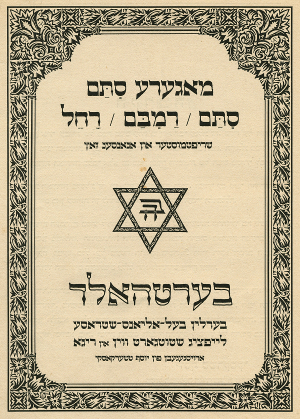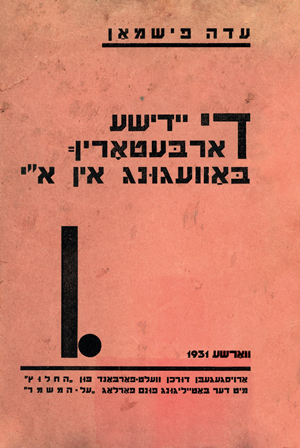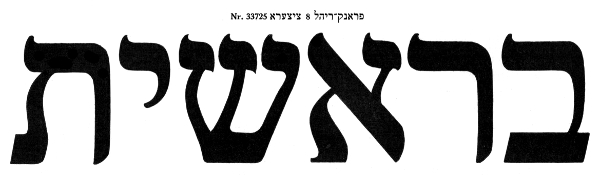
Hebräische Schriftgestaltung im Kontext von Buchkunstbewegung und ‹Neuer Typographie›
Unter dem Schlagwort der ‹Neuen Buchkunst› formierten sich in Deutschland um 1900 Bestrebungen zu einer Erneuerung der Buch- und Schriftgestaltung nach dem Vorbild der englischen Arts-and-Crafts-Bewegung. Diese Erneuerungsbewegung verstand sich als Reaktion auf die in Deutschland vor allem nach der Reichsgründung 1871 rasant vorangetriebene Industrialisierung. Die Ablösung der handwerklich-traditionellen durch eine zunehmend technisierte Produktion betraf neben diversen Gütern des täglichen Gebrauchs auch die Buchherstellung. Folgt man den zeitgenössischen Kommentatoren führte dies zu einem qualitativen Niedergang der neben dem Material auch die Ästhetik betraf. Neben den verschiedenen industriell hergestellten Gütern wurde um die Jahrhundertwende auch beim Buch die Forderung nach einer zeitgemäßen, material- und zweckgebundenen Form laut. Diese Forderung betraf all seine Elemente und nicht zuletzt auch die Druckschriften. So wurde damit begonnen zur Schriftgestaltung Künstler herbeizuziehen. Die auf diese Weise erzielten Resultate waren in einer ersten Phase noch stark von der Formensprache des Jugendstils beeinflusst. Nach Ende des Ersten Weltkriegs setzte dann allerdings eine deutliche Hinwendung zu historischen, stärker handschriftbasierten Formen ein. Dies verdankte sich zu einem großen Teil dem Einfluss des englischen Schriftkünstlers Edward Johnston. Der an der Londoner School of Arts and Crafts lehrende Johnston und seine auf den Formen alter Handschriften fussende kalligraphische Methode war in Deutschland vor allem durch das Wirken seiner Schülerin und Übersetzerin Anna Simons bekannt geworden. In der Folge wurden Fragen der Schriftgestaltung dezidiert traditionsgebunden behandelt und vor allem durch die intensive Beschäftigung mit historischen Formen bestimmt. Mit dieser Tendenz, welche das gestalterische Selbstverständnis sowohl von Franzisca Baruch als auch von Henri Friedlaender nachhaltig prägte, brach um 1925 schliesslich die ‹Neue Typographie›, die eine neue, wahrhaft industrielle Ästhetik propagierte.
Schriftgestaltung und kunstgewerbliche Ausbildung in Deutschland
Ein wichtiger Träger dieser ästhetischen Tendenz waren Kleinpressen nach dem Modell der in den 1890er Jahren von William Morris in Hammersmith bei London betriebenen Kelmscott Press. Hierbei handelte es sich um Betriebe, bei denen die Arbeitsteilung zwischen Verlag, Gestaltung und Herstellung zugunsten einer ganzheitlichen Praxis weitgehend aufgehoben war. Auf diese Weise wollte man einem möglichst idealen Einklang von Buchinhalt und Buchgestalt erreichen. Die Pressedrucke sollten als Vorbilder wirken und so dazu beitragen, die formale, handwerkliche und künstlerische Qualität von Büchern, Zeitschriften und nicht zuletzt von Druckschriften nachhaltig zu verbessern. Tatsächlich gelang es in Deutschland den Pressen sich in diesem Sinn als ‹Versuchsanstalten› zu positionieren und es sind in der Folge eine Reihe größere Unternehmen die zu Trägern der buchkünstlerischen Erneuerung werden.[1] Als beispielhaft für das erfolgreiche Zusammenspiel von bibliophiler Reformbewegung und Massenproduktion kann neben dem Insel Verlag mit seiner ‹Bücherei› auch die Schriftgießerei Gebr. Klingspor in Offenbach gelten. Das weltweit tätige Unternehmen, das 1907 auch zu den Gründern des Deutschen Werkbunds gehörte, war bekannt dafür, ausgesprochen hohen Wert auf die ästhetische Qualität seiner Schriften zu legen. In den 1920er Jahren beschäftigte das Unternehmen mit Rudolf Koch einen der herausragenden Schriftkünstler Deutschlands, der mit seiner im Rahmen dieser Zusammenarbeit entfalteten gleichsam expressiven wie im Handwerk verwurzelten Schriftgestaltung nicht nur für Henri Friedlaender ein wichtiges Vorbild war.
Anzeige für die Schriftgießerei Gebr. Klingspor unter Verwendung der Schriften ‹Neuland› und ‹Koch-Antiqua› von Rudolf Koch, 1926.
Das Vorhandensein einer graphischen Industrie mit ausgesprochenem Qualitätsbewusstsein verband sich in Deutschland zu dieser Zeit mit der Grundlagenbildung in Schriftkursen an einer Reihe von Kunstgewerbeschulen, welche die vom Werkbund ausgehenden Impulse bald aufgenommen und in die Ausbildung integriert hatten. So bestand beispielsweise in Leipzig, dem Zentrum der deutschen Buchproduktion, die Akademie für graphische Künste und Buchgewerbe.[2] Hier bewarb sich 1925 der 21-jährige Henri Friedlaender. Friedlaender hatte zu diesem Zeitpunkt bereits seit drei Jahren in einer Berliner Druckerei gearbeitet. Seinem Bewerbungsschreiben zufolge, war für ihn dabei vor allem, der Drang bestimmend, «mich in künstlerisch-handwerklicher Hinsicht so auszubilden, daß ich mit Erfolg in einer ‹Presse› oder an ähnlicher Stelle mitarbeiten kann.»[3] Für Friedlaender, der die Leipziger Akademie mit bestandener Meisterprüfung als Schriftsetzer im Juli 1926 nach weniger als einem Jahr bereits wieder verliess, war es der Unterricht in Entwerfen und Schriftkunst bei Hermann Delitsch an der Akademie, der ihn nachhaltig prägen sollte.[4]Delitsch war ein Pionier im Feld der kunstgewerblichen Lehre der Schrift. Im Rahmen des von ihm an der Akademie aufgebauten Schriftkurses betrieb er auch ausgiebig schriftgeschichtliche Studien und baute eine umfangreiche Sammlung von Beispielen geschriebener und gedruckter lateinischer Schriften auf. Der Schriftunterricht bestand hauptsächlich im sorgfältigen Nachschreiben dieser Vorbilder. Delitschs systematische Vorbildsammlung war es auch, die Friedlaender dazu inspirierte, eine entsprechende Sammlung hebräischer Schriften aufzubauen.[5]
Übungsblätter von Henri Friedlaender aus dem Kurs von Hermann Delitzsch an der Akademie für graphische Künste und Buchgewerbe in Leipzig, 1925/26 [Klingspor-Museum Offenbach, Sammlung Henri Friedlaender].
Die Schreibkunst wurde auch an der Unterrichtsanstalt des Staatlichen Kunstgewerbemuseums Berlin gepflegt, an die im Sommersemester 1918/19 Franzisca Baruch nach bestandener Eignungsprüfung in die Fachklasse für Buchkunst und Grafik aufgenommen wurde. In Berlin hatte sich der langjährige Leiter der Bibliothek des Kunstgewerbemuseums, Peter Jessen, welcher der jungen Buchkunstbewegung in Deutschland publizistisch und in Form von öffentlichen Vorträgen den Weg bereitet hatte, mit seiner Überzeugung durchgesetzt, dass bei Fragen der Buchgestaltung der Schrift das Primat vor der Verzierung eingeräumt werden müsse – dies im Zusammenhang mit einem sich oftmals auf Buchschmuck beschränkenden Begriff von Buchgestaltung. Jessen vertrat mit Johnston die Meinung, dass eine Hebung der Qualität der Druckschriften dabei nicht ohne eine allgemeine Pflege der Schreibkunst zu erreichen sei.[6] Die neben Jessen in Fragen der Schriftgestaltung bestimmende Figur an der Unterrichtsanstalt war der renommierte Schriftkünstler Emil Rudolf Weiß. Weiß, der zur Zeit von Baruchs Studien in Berlin u.a. mit einer Sondernummer der Fachzeitschrift Archiv für Buchgewerbe und Gebrauchsgrafik geehrt wurde,[7] war als Autodidakt vom Jugendstil hergekommen und hatte danach Schriftkurse bei Anna Simons besucht. Von Jessen war er zudem mit den Druckschriften der Wiegendruckzeit vertraut gemacht worden.[8] So zeichnen sich die schriftkünstlerischen Arbeiten Weiß’ auch durch einen dezidierten Traditionsbezug aus. Der Kulturhistoriker Walther Georg Oschilewski spricht in diesem Zusammenhang von «Schriftdenkmälern», die Weiß «auf dem Weg eines eigenschöpferischen Umformungsprozesses» in neuer Gestalt in seinen Arbeiten wieder aufleben lasse.[9] An der Unterrichtsanstalt des Kunstgewerbemuseums unterrichtete Weiß allerdings nicht als Grafiker, sondern als Kunstmaler und Leiter der Fachklasse für Dekorative Malerei und Musterzeichnen. Durch Vermittlung von befreundeten Lehrern war sein Einfluss auf die Schriftgestaltung ein zwar indirekter, aber deshalb nicht weniger nachhaltig. So hatte Franzisca Baruch in ihrem ersten Semester an der Unterrichtsanstalt Abendkurse in Schrift bei Else Marcks-Penzig besucht,[10] die eine Meisterschülerin von E. R. Weiß gewesen war und in Zusammenarbeit mit diesem auch Bucheinbände und Schutzumschläge für die Verlage S. Fischer und Insel gestaltet hatte.[11] Die Tasache, dass die begabte Gestalterin, die während der Kriegsjahre an der Unterrichtsanstalt erfolgreich als Lehrerin tätig war, nach Kriegsende bald wieder durch einen Mann ersetzt wurde, dürfte der jungen Studentin die prekäre Situation berufstätiger Frauen deutlich vor Augen geführt haben. Nach drei Jahren in der von Emil Orlik geleiteten Fachklasse für Buchkunst und Grafik wechselte Baruch 1922 in die damals neugeschaffene Fachabteilung «Gebrauchsgraphik», wo Ernst Böhm ihr Lehrer wurde. Böhm der sich mit Illustrationen und als Entwerfer von Bucheinbänden und Briefmarken einen Namen gemacht hatte war mit E.R. Weiß gut befreundet und während er als Grafiker durchaus einen eigenen Stil entwickelt hatte, der sich u.a. durch Anleihen an ‹naive› Formen und Motive der Volkskunst auszeichnete, bleiben seine schriftkünstlerischen Arbeiten gänzlich in dem von Weiß abgesteckten Rahmen.[12]
Franzisca Baruchs Beschäftigung mit den Formen der hebräischen Schrift – die gesprochene Sprache sollte sie sich erst viel später und eher schlecht als recht aneignen – fällt in die ersten Jahre als Schülerin der Unterrichtsanstalt. Hier nutzte sie offenbar intensiv die, durch die reichen Bestände der Kunst- und vor allem der Staatsbibliothek in Berlin gegebene Möglichkeit zum Selbststudium, wie ein in ihrem Nachlass befindliches Skizzenbuch nahelegt.[13] Analog zu den Bestrebungen einer schöpferischen Wiederbelebung verschütteter Traditionsbestände lateinischer Antiqua- und deutscher Frakturschriften, wie sie an der Unterrichtsanstalt und in bibliophilen Kreisen propagiert wurde, näherte sie sich dem Hebräischen über die in mittelalterlichen Handschriften und Frühdrucken zu findenden Formen. Ausgehend von diesen historischen Vorbildern entwickelte sie in der ersten Hälfte der 1920er Jahre eine Reihe kalligraphischer Stile, mit denen sie sich als erste hebräische Schriftkünstlerin Berlins etablierten konnte, und mit ‹Stam› schliesslich auch eine gegossene Schrift für den Druck, produziert 1928 von der in Berlin ansässigen Gießerei H. Berthold AG.[14] Die Type orientierte sich am Modell der im Jahr 1526 in Prag gedruckten Pessach Haggadah des Gershom Kohen. Als erfolgreiche typographische Aktualisierung einer aschkenasischen Quadratschrift aus dem 16. Jahrhundert passt Oschilewskis Begriff des ‹Schriftdenkmals› auch für Baruchs ‹Stam›.
Titel einer Broschüre zu der von Franzisca Baruch entworfenen Schrift ‹Stam› und ihrer Variationen, um 1925.
Berlin als Zentrum neuhebräischer Buchkunst
Die Spezialisierung der jungen Schriftkünstlerin auf das Hebräische fällt in eine Zeit äusserst lebhafter hebräischer und jiddischer Publikationstätigkeit in Berlin, einer Stadt die nach dem Ende des Ersten Weltkriegs zu einer wichtigen Station der jüdischen Migration aus Osteuropa geworden war. Unter den Migranten befanden sich auch eine Reihe von Schriftstellern und Verlegern, deren Aktivitäten Berlin in den Jahren zwischen 1919 und 1924 zu einem Zentrum einer die Sprache und ihren Gebrauch revolutionierenden jiddischen und hebräischen Literatur machten.
In diesem Zusammenhang steht auch die Publikation Katalog hebräischer und jüdischer Schriften, der H. Berthold AG, die weltweit erste ausschließlich hebräische Druckschriften enthaltende Publikation einer Schriftgießerei.[15] Neben einer beinahe luxuriös zu nennenden Ausstattung zeichnete sich der Katalog auch durch eine Vielzahl von praktischen Anwendungsbeispielen für die angebotenen Schriften aus – in den Worten des Herausgebers dazu bestimmt, «dem hebräischen Typographen […] den Anschluss an die abendländische Buchdruckerei zu erleichtern»[16]. Im Zentrum des Berthold-Katalogs stand dabei die in sämtlichen gebräuchlichen Größen angebotene ‹Frank-Rühl›, die mit einigem Recht als erste modern-hebräische Druckschrift, gelten kann. Mit seinem Entwurf hatte ihr Schöpfer, der Leipziger Kantor Rafael Frank, vor allem die nationaljüdische Bewegung im Blick, von welcher der Impuls ausging, aus der Sprache des religiösen Ritus, eine lebendige Alltags- und Literatursprache zu schaffen.[17] Von der Schriftgießerei C. F. Rühl in Leipzig bereits 1910 gegossen, erlangte die ‹Frank-Rühl› im Zuge der Übernahme der kleinen Leipziger Firma durch die weltweit tätige Berthold AG ihre Stellung als mit Abstand meistverwendete hebräische Druckschrift. Dieser Erfolg hängt auch damit zusammen, dass von den vor 1948 neugeschaffenen hebräischen Typen keine als Grundschrift für den Werksatz brauchbar war, da eine solche äusserst hohen Ansprüchen genügen muss, sie hat auch in kleinen Größen leicht lesbar und vielfältig verwendbar zu sein. Schriften wie Franzisca Baruchs ‹Stam› wurden nicht für Mengensatz eingesetzt, sondern lediglich als sogenannte Akzidenzschriften für den wirkungsvoll gestalteten Druck kürzerer Texte wie Werbeanzeigen, Geschäftsdrucksachen, Titel oder Zeitungsköpfe.
Schriftbeispiel der ‹Frank-Rühl-Hebräisch›, 1924.
Im Jahr des Erscheinen des Berthold-Katalogs gründete sich in Berlin auch die erste Organisation jüdischer Bibliophilen, die sich in Anlehnung an eine im 15. Jahrhundert in Italien aktive Druckerfamilie «Soncino-Gesellschaft der Freunde des jüdischen Buches» nannte. Die Gesellschaft hatte sich die Aufgabe gestellt, «die jüdische Buchherstellung durch Beratung und Kritik auf den der jüdischen Allgemeinkultur entsprechenden Stand zu heben und dahin zu wirken, daß die Form des jüdischen Buches als repräsentativ für das jüdische Geistesleben gelten darf».[18] Aus den Reihen dieser von deutschsprachigen Juden geprägten Vereinigung kam eine erste dezidierte Kritik an den von der Berthold AG breit vermarkteten hebräischen Schriften. Insbesondere die ‹Frank-Rühl› sah man weniger als Ausdruck der kulturellen Erneuerung des Judentums, denn als «verspätetes Kind des Jugendstiles».[19] Eine neue hebräische Druckschrift, so die Überzeugung in diesen Kreisen, könne nur auf der Grundlage historischer Vorbilder entwickelt werden. Schliesslich beschloss die Gesellschaft auf diesem Gebiet selber aktiv zu werden. Für den Druck einer luxuriösen hebräischen Bibel wurde 1927 der populäre nichtjüdische Buchkünstler Marcus Behmer mit der Gestaltung einer Type beauftragt. Als Modell wurde dabei, wie bei Baruchs ‹Stam›, ebenfalls die Type der Prager Haggadah von 1526 gewählt.
Bauhaus und «Neue Typographie»
Während in den Kreisen der jüdischen und nichtjüdischen Bibliophilen dem Ideal einer historisierenden Schriftgestaltung und Typographie gehuldigt wurde, formierte sich in Avantgardekreisen ein Verständnis von Gestaltung, das an diese zuallererst den Anspruch stellt, zeitgemäß zu sein. Analog zum funktionalistischen ‹Neuen Bauen› ist von der ‹Neuen Typographie› die Rede. Beeinflusst vom russischen Konstruktivismus und der niederländischen Stjil-Bewegung wird verschiedenenorts der Versuch unternommen, eine der industriellen Produktionsweise entsprechende typographische Ästhetik zu entwickeln. Der Losung technischer Rationalität folgend sollen die Buchstabenelemente dabei auf einige wenige Grundformen reduziert werden. Ein wichtiger – wenngleich auch keinesfalls der einzige – Kristallisationsort für diese Tendenz war in Deutschland das 1919 in Weimar begründete und 1925 nach Dessau umgezogene Bauhaus. Eine Schlüsselrolle spielte dabei László Moholy-Nagy, der hier 1923 die Leitung des gestalterischen Vorkurses, der von seinem Vorgänger Johannes Itten eingeführten beiden Grundlehrsemester, übernahm. Moholy-Nagy vertrat die Meinung, dass die bisher grösstenteils traditionsbestimmten Schriftformen grundlegend umgestaltet werden müssten. Mit der Einstellung von Herbert Bayer, Josef Albers und Joost Schmidt, drei ehemaligen Studenten Moholy-Nagys, wurden seine revolutionären typographischen Ideen 1925 endgültig zur Lehrmeinung am Bauhaus.[20] Der für alle Vorkursstudierenden obligatorische Schriftunterricht wurde Joost Schmidt übertragen. Im Gegensatz zum Unterricht in Leipzig oder Berlin wurde in dem «Schrift und Reklame» benannten Kurs nicht mehr die Handschrift als formale Grundlage der Buchstaben vermittelt, sondern eine an geometrischen Formen orientierte Konstruktion.[21] [Abb. 5] Wie der Name seiner Unterrichtseinheit nahelegt, stand Schmidts Auffassung von Schrift in engem Zusammenhang mit den Forderungen des sich zu dieser Zeit rasant entwickelnden Werbewesens. Schrift soll rational zu entwickeln sein, einheitlich und deutlich lesbar. Auf dieser Grundlage wurden am Bauhaus eine Reihe geometrischer Alphabete entwickelt, von denen allerdings keine je in Lettern geschnitten wurde. So wurden am Bauhaus die in Avantgardekreisen verbreiteten Ideen zur Schriftgestaltung zwar gebündelt und systematisiert, die Übertragung dieser Ideen in brauchbare und kommerziell nutzbare Schriften aber wurde hauptsächlich von anderen Instanzen geleistet.[22] So revolutionär sich die Ideen der Neuen Typographie für den weiteren Bereich der Gebrauchsgrafik erwiesen, so gering war aber letztlich ihre Auswirkung auf das literarische Buch, dessen Form im Zentrum der Bemühungen sowohl von Friedlaender als auch Moritz Spitzer stand. Das mag damit zu erklären sein, dass dieser Kernbereich der Buchgestaltung seiner Natur gemäss auf Stetigkeit angewiesen ist und wenig geneigt, sich rasch heftig zu wandeln.
Konstruierte Schrift von Joost Schmidt, um 1925 [Bauhaus-Archiv / Museum für Gestaltung, NL Joost Schmidt, Mappe 34].
Eine hebräische Schrift im Geist der Bauhaus-Typographie ist die 1929 in Warschau gegossene ‹Chaim›,[23] der, im Gegensatz zu ihren direkten Vorbildern, eine äusserst erfolgreiche Karriere als Akzidenzschrift beschert war. Die vollständig rundungslose, serifen- bzw. endstrichlose Schrift ist aus Balken in gleichbleibender Stärke konstruiert und stellt einen Bruch mit sämtlichen Regeln traditionsbestimmter Schriftgestaltung dar. Ihr Schöpfer, der im polnischen Schlesien geborene Jan Le Witt, hatte 1927 Tel Aviv besucht und hier den durch die um 1924 einsetzende Einwanderungswelle ausgelösten Boom erlebt.[24] Mit einem regen kulturellen und kommerziellen Leben war in der ‹ersten hebräischen Stadt› auch ein Bedürfnis nach modern gestalteter Werbung entstanden. Bald nach seiner Rückkehr nach Warschau 1928, wo er sich als Werbegrafiker betätigte, begann Le Witt mit den Entwürfen für eine hebräische Druckschrift, die ähnlich zeitgemäß wirken sollte wie die 1927 von der Bauerschen Schriftgießerei in Frankfurt erfolgreich als «Schrift unserer Zeit» vermarktete geometrische Groteskschrift ‹Futura› von Paul Renner. Das Ergebnis – ganz im Gegensatz zu Renners vielseitiger Schrift, deren Zeichen zwar aus Kreisen und geraden Linien konstruiert scheinen, in Wahrheit aber den Sehgewohnheiten entsprechend angepasst sind – war eine Schrift von fast brutal zu nennender Modernität, die sich in Palästina schon bald sehr großer Beliebtheit als Auszeichnungsschrift erfreute.
‹Chaim›, verwendet auf einem konstruktivistisch gestalteten Umschlag eines in Warschau gedruckten Buches in Jiddischer Sprache, 1931.
Eine weitere hebräische Schrift im Sinne der Neuen Typographie, die dieser Tatsache Rechnung trug, war die 1935 von der Firma Ludwig & Mayer in Frankfurt am Main in zwei Schnitten gegossene Schrift ‹Aharoni› – benannt nach ihrem Schöpfer, dem in Tel Aviv aktiven Werbegrafiker Tuvia (Tadek) Aharoni. Die ausschliesslich in Palästina vermarktete Schrift stellt eine Verfeinerung der grob-elementaren ‹Chaim› dar. Mit ihrer die Leserichtung betonenden Ausrichtung brachte die ‹Aharoni› eine gegenüber LeWitts Schrift deutlich verbesserte Lesbarkeit und vermittelt auch einen ungleich eleganteren Gesamteindruck. Sie stellt ein würdiges Gegenüber für die damals modernen lateinischen Grotesk- und Egyptienne-Schriften dar. Die Tatsache, dass bei diesen Schriften alle Linien jeweils nahezu die gleiche Stärke aufweisen, machte es möglich, dass die gewünschte formale Angleichung der beiden Schriftsysteme erreicht werden konnte, ohne dabei das hebräische dem lateinischen unterzuordnen. Folgt man einem zeitgenössischen Bericht in der englischsprachigen Palestine Post, wurden die radikal modernistischen Formen des Hebräischen in Palästina auch im Bereich der Werbung begeistert aufgenommen. So schreibt der britische Autor, dass die Vorliebe für serifenlose, monolineare Schriften hier zu einer Form des Hebräischen geführt habe, das mit dessen traditionellen Formen «so wenig zu tun habe, wie der moderne europäische Jude mit den antiken Israeliten».[25] Neben dem zu dieser Zeit zweifellos herrschenden Mangel an zeitgemäßen hebräischen Druckschriften, lässt sich der Siegeszug der modernistischen Tendenz zu einem gewissen Grad auch mit der damals in der jüdischen Gemeinschaft in Palästina dominanten Ideologie des sozialistischen ‹Arbeiterzionismus› erklären. Diese wies Tradition als bestimmenden Faktor entschieden zurück und betonte die Möglichkeit einer radikalen Transformation von Kultur und Gesellschaft.[26]
‹Aharoni›: Schriftmuster, 1936.
Abschied von Europa
Auch wenn es in Jerusalem seit 1906 eine Kunstgewerbeschule gab, haben sich die modernistischen Tendenzen in Palästina ausserhalb dieser Institution entwickelt. An der Bezalel wurde bis zu ihrer zwischenzeitlichen Schliessung 1929 hauptsächlich kunstgewerbliche Souvenirs und dekorative Kunstgegenstände hergestellt. Der dabei zur Anwendung kommende Stil war geprägt von einem romantisierenden Bild des Orients.[27] Eine Auseinandersetzung mit Herausforderungen der Moderne fand an der Bezalel kaumstatt. Im Bereich der Schrift- und Buchkunst hatte man sich weitgehend auf die Gestaltung von Illustrationen und ornamentalem Buchschmuck beschränkt. Die Schule war deshalb ohne großen Einfluss auf eine Weiterentwicklung der hebräischen Druckschriften oder auf die allgemeine Qualität der im damaligen Palästina produzierten Bücher geblieben. Dies änderte sich erst als die Bezalel 1935 grundlegend reformiert wiedereröffnet wurde. Unter ihrem neuen Leiter, dem Berliner Künstler Josef Budko, wurde die Schule zum Anlaufpunkt für eine Reihe aus ihrer Heimat geflohener deutsch-jüdischer Gestalter, die sich oftmals ihre tiefe Verbundenheit mit der deutschen typographischen Kultur über den Zivilsationsbruch hinaus bewahrt hatten.
Nicht zuletzt wurde an der Neuen Bezalel auch ein Schriftkurs mit hebräischem Schwerpunkt eingerichtet. Hierzu wurde der aus Galizien stammende Yerachmiel Schechter als Lehrer berufen, der in der Zeit zwischen 1921 und 1927 mit allen kalligraphischen Arbeiten des Zionistischen Weltkongresses betraut gewesen war. Der Unterricht des Autodidakten Schechters an der Bezalel folgte weitgehend der historisch ausgerichteten Methode Edward Johnstons.[28] Als Moritz Spitzer um 1940 in Jerusalem an seinen ersten Veröffentlichungen zu arbeiten begann, hatte diese Initiative an der Neuen Bezalel aber offenbar noch wenig Auswirkungen auf die Kultur des gedruckten hebräischen Buches gezeigt.[29] Die Druckereien im Land waren schlecht mit grösstenteils aus polnischer oder deutscher Produktion stammendem Schriftenmaterial ausgestattet. Für den hebräischen Werksatz standen grösstenteils nur veraltete und abgenutzte Typen zur Verfügung, wobei die Auszeichnungsschriften kaum mit den verfügbaren Grundschriften korrespondierten, so dass man sie nicht gut für Überschriften, Titeleien oder Initialen verwenden konnte. Da während des Zweiten Weltkriegs weder Druckmaschinen noch typographisches Material ersetzt werden konnten verschlechterte sich der Zustand der Typen eher noch. Zumindest äussert sich Gerschom (Gustav) Schocken, der hier zehn Jahre zuvor die Leitung der von seinem Vater Salman gekauften hebräischen Tageszeitung Haaretz inklusive der hauseigenen Druckerei übernommen hatte, 1946 entsprechend.[30] Beim grössten Teil der hier zur Verfügung stehenden hebräischen Schriften handle es sich um «hässliche und verdorbene Nachfahren» der ursprünglich schönen Typen, die im sechzehnten Jahrhundert in Italien geschnittenen wurden. Mit der Ausnahme von ein, zwei, einzig für Werbezwecke geeigneten Alphabeten, so Schocken 1946, habe die Renaissance der hebräischen Sprache bisher noch keine neuen Schriften hervorgebracht. Deshalb sei eine der großen Aufgaben, vor denen das jüdische Druck- und Verlagswesen in Palästina stehe, die Herstellung neuer hebräischer Druckschriften.[31]
Die Herausforderung, der sich in Folge alle drei in dieser Ausstellung behandelten Gestalter auf unterschiedliche Weise annahmen, bestand dabei darin, jenseits der Dichotomie von Traditionalismus und Gegenwärtigkeit gleichsam ‹zeitoffene› gestalterische Lösungen zu finden – und damit Schriftformen zu schaffen, die sowohl der weit zurückreichenden Tradition als auch dem grundlegend veränderten Status der hebräischen Sprache gerecht werden können.
Philipp Messner, 2015
Erschienen in hebräischer und englischer Übersetzung im Katalog zur Ausstellung «דפוסים משתנים | New Types – Three Pioneers of Hebrew Graphic Design».
[1] Zu den Besonderheiten der deutschen Druckkultur im 20. Jahrhundert, siehe Robin Kinross: Modern Typography: An Essay in Critical History (London 1992), S. 67–79.
[2] Zur Geschichte der Leipziger Akademie, siehe Julia Blume und Fred Smeijers: Ein Jahrhundert Schrift und Schriftunterricht in Leipzig (Leipzig, 2010).
[3] Henri Friedlaender: Handschriftlicher Lebenslauf, 10.09.1925, Staatsarchiv Leipzig, 20199/103.
[4] Vgl. Kurt Löb: Exil-Gestalten. Deutsche Buchgestalter in den Niederlanden, 1932–1950 (Arnhem, 1995), S. 42.
[5] Vgl. Henri Friedlaender an Siegfried Guggenheim, 23.06.1947, Leo Baeck Institute Archives, Siegfried Guggenheim Collection, AR 180/I/16.
[6] Vgl. Peter Jessen: «Die Schrift», in: Archiv für Buchgewerbe 1, no. 4 (1899), S. 149.
[7] Archiv für Buchgewerbe und Gebrauchsgraphik 59, no. 9/10 (1922).
[8] Vgl. Walther G. Oschilewski: «E. R. Weiß und die Schönheit der Formen», in: Imprimatur NF 2 (1960): S. 5–13, 10.
[9] Ebd.
[10] Vgl. Franzisca Baruch: Zensurbogen Sommersemester 1918/19, Universität der Künste Berlin, Universitätsarchiv, 7/350.
[11] Vgl. Marie Marcks: Else Marcks-Penzig (München, 1995), S. 8.
[12] Vgl. Günter Scherbarth, «Erinnerungen an den Maler, Grafiker und Lehrer Ernst Böhm (1890–1963)», in: Myosotis 8, no. 2/3 (1993), S. 28-34.
[13] Franzisca Baruch: Skizzenbuch, Israel Museum Jerusalem, Archiv Franzisca Baruch, B14.1274.
[15] Ders. (Hg.): Katalog hebräischer und jüdischer Schriften der Schriftgießerei H. Berthold AG (Berlin, 1924); siehe auch Stephen Lubell: «Joseph Tscherkassky – Orientalist and Typefounder», in: Gutenberg-Jahrbuch 71 (1996), S. 222–239.
[16] Tscherkassky (1924), n.p.
[17] Vgl. Rafael Frank: Über hebräische Typen und Schriftarten (Berlin, 1926), S. 21; Neben der Frank-Rühl geht auch die 1924 von Berthold publizierte, in ihrer Art präzendenzlose, monolineare Schrift Mirjam auf Entwürfe des 1920 verstorbenen Frank zurück: Vgl. Ittai Joseph Tamari: «Rafael Frank und seine hebräischen Druckschriften», in: M. Unger (Hg.): Judaica Lipsiensia (Leipzig, 1994), S. 70–78.
[18] Werbebrief der Soncino-Gesellschaft der Freunde des jüdischen Buches, [1924], Jüdisches Museum Berlin, Sammlung Soncino-Gesellschaft, DOK 93/502/7–14; zur Soncino-Gesellschaft allgemein, siehe: Karin Bürger, Ines Sonder, und Ursula Wallmeier (Hgs.): Soncino-Gesellschaft der Freunde des jüdischen Buches. Ein Beitrag zur Kulturgeschichte (Berlin, 2014).
[19] Herrmann Meyer: «[Rezension zu Frank, Rafael: Über hebräische Typen und Schriftarten, 1926]», in: Monatsschrift für Geschichte und Wissenschaft des Judentums 70, no. 5 (1926): S. 428–429, 429. [PDF]
[20] Vgl. Robin Kinross: «Das Bauhaus im Kontext der Neuen Typographie», in: Ute Brüning (Hg.): Das A und O des Bauhauses (Leipzig, 1995), S. 9–14.
[21] Vgl. Ute Brüning: «Unterricht Joost Schmidt. Vorkurs ‹Schrift und Reklame›», in: Ebd., S. 193–205.
[22] Robin Kinross: «Das Bauhaus im Kontext der Neuen Typographie», in: Ebd., S. 12.
[23] Verschiedentlich wird als Urheber der Schrift auch der aus Ungarn stammende Pesach Ir-Shay genannt. Dass eine entsprechende Schrift Ir-Shays von einer Schriftgießerei produziert worden wäre, dafür gibt es nach Wissens des Autors keinerlei Anzeichen. Chaim wurde vom Warschauer Unternehmen Jan Idźkowski i S-ka 1929 gesetzlich Schützen lassen. Vgl. Marian Misiak, «Chaim: owoc wielokulturowej Warszawy», in: Ders. (Hg.): Paneuropa, Kometa, Hel. Szkice z historii projektowania liter w Polsce (Kraków 2015), S. 76–81.
[24] Vgl. Herbert Read, Jean Cassou und John Smith: Jan Le Witt (Paris, 1972), S. 138.
[25] «[...] a species of typography which is as unlike traditional Hebrew as the modern European Jew is unlike the ancient Israelites», Louis Katin: «Neonising the Hebrew Alphabet», in: Palestine Post, 19.07.1935, S. 6.
[26] Zur revolutionierenden Rolle der hebräischen Sprache im Zusammenhang mit dem zionistischen Projekt siehe: Benjamin Harshav: Language in Time of Revolution (Berkeley, 1993).
[27] Vgl. Dalia Manor: «Orientalism and Jewish National Art: The Case of Bezalel,» in: I. D. Kalmar und D. J. Penslar (Hgs.): Orientalism and the Jews, (Waltham, Mass., 2005), S. 142–161.
[28] Vgl. Leila Avrin: «Calligraphy, Modern Hebrew,» in Encyclopaedia Judaica, 2nd Edition, (Detroit and Jerusalem, 2007), Bd. 4, S. 366–373.
[29] Vgl. Israel Soifer: «The pioneer work of Maurice Spitzer», in: The Penrose Annual 63 (1970), S. 127–145.
[30] Gustav Schocken: «Printing and Publishing», in: J. B. Hobman (Hg.): Palestine’s Economic Future: A Review of Progress and Prospects, (London, 1946), S. 244–252.
[31] Ebd.